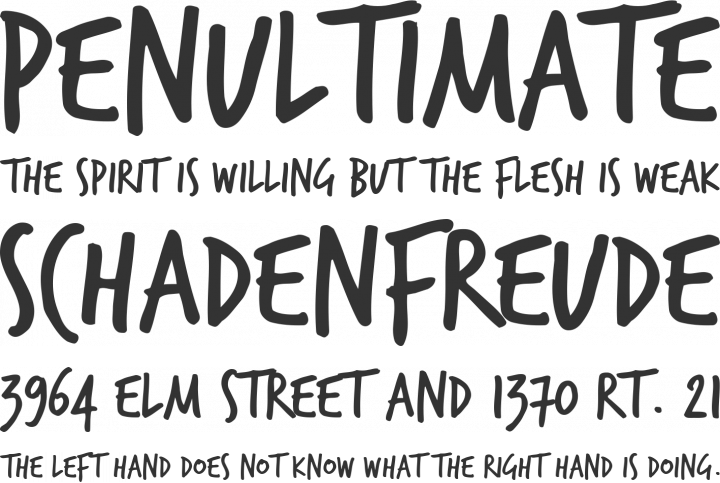
Modewelle: Condensed Comic-Schriften in All Caps und Small Caps für Nahrung, Gaststätten und Genuß (NGG)??
:tuschel: Es geht ja auch nicht um Marker-Schriften, sondern um "Modewelle: Condensed Comic-Schriften …"
Uwe, blättere doch mal in diesem Blog etwas in die Vergangenheit:
Die Annette hat das Aufkommen dieser bestimmten Kategorie ebenfalls sehr früh registriert.
Mindestens ein Korrekturdurchgang hätte nicht geschadet. Nicht nur wegen der vielen Schreibfehler. Nur drei Anmerkungen:
Seite 26: Der Retro-Look, der heute Vintage heißt, brachte damals auch
das alten Handwerk wie Letterpress, was in deutscher Sprache schon
vor Gutenberg profan Briefdruck genannt wird, wieder inMode.
Kleiner Hinweis, weil es mein Gebiet ist: »Letterpress« als Prägedruck ist seit 2009 breit etabliert, das war das erste Jahr, in dem ich mehr davon druckte als vom Bleisatz und die Zahl neuer Werkstätten deutlich höher wurde. Buchdruck (nicht »Briefdruck«) mit beweglichen Lettern vor Gutenberg gab es nicht. Der Mann hat das erfunden. Was sollte an dem Begriff profan sein?
S. 28: Vorsicht mit der
Nutzung dieses Designs, besonders wenn es um nicht kommerzielle
und/oder gemeinnützige Projekte geht. Das Design kann vom Betrachter
mit Gewinnerzielungsabsichten bis hin zur Gier assoziiert
werden.
Ob ich das den Desigern von Hochzeitseinladungen wirklich sagen sollte?
S. 31: So benutzteMc Donalds eine Pinselschrift aus
einem dieser Pakete und Lindt-Schokolade plünderte für sein Design
die kompletten Setzkästen.
Ein deutscher Antiqua-»Setzkasten« enthält 125 Fächer für die Zeichen einer Schrift in einem Schnitt und einer Größe. Viel zu »plündern« gibt es da nicht.
Mindestens ein Korrekturdurchgang hätte nicht geschadet. Nicht nur wegen der vielen Schreibfehler.
Geduld! Rechtschreibung wird überbewertet und das sind erst mal nur Notizen. Wichtiger sind noch die inhaltlichen Fehler, da ich beim Abfassen immer irgend wann mal betriebsblind werde. Ich habe daher Deine drei Kritikpunkte durchgelesen und zwei davon auch schon berücksichtigt. Möglicherweise kommt noch der eine oder andere Hinweis.
Seite 26: Der Retro-Look, der heute Vintage heißt, brachte damals auch
das alten Handwerk wie Letterpress, was in deutscher Sprache schon
vor Gutenberg profan Briefdruck genannt wird, wieder inMode.
Kleiner Hinweis, weil es mein Gebiet ist: »Letterpress« als Prägedruck ist seit 2009 breit etabliert, das war das erste Jahr, in dem ich mehr davon druckte als vom Bleisatz und die Zahl neuer Werkstätten deutlich höher wurde. Buchdruck (nicht »Briefdruck«) mit beweglichen Lettern vor Gutenberg gab es nicht. Der Mann hat das erfunden. Was sollte an dem Begriff profan sein?
Eingebaut ... Hinweis auf Briefdruck verworfen und Definition Letterpress von 2009 nachgetragen.
Der Retro-Look, der heute Vintage heißt, brachte damals auch
das Handwerk wie Letterpress wieder in Mode. Mit Letterpress sind
seit etwa 2009 Akzidenzen mit Prägedruck gemeint.
S. 31: So benutzteMc Donalds eine Pinselschrift aus
einem dieser Pakete und Lindt-Schokolade plünderte für sein Design
die kompletten Setzkästen.
Ein deutscher Antiqua-»Setzkasten« enthält 125 Fächer für die Zeichen einer Schrift in einem Schnitt und einer Größe. Viel zu »plündern« gibt es da nicht.
Ok, ich meinte den kompletten Bestand an virtuellen Setzkästen, also das komplette Paket an Schriften.
Anfang 2016 tauchten die ersten Schriften und Kombinationen aus
solchen Paketen auf. So benutzte Mc Donalds eine Pinselschrift aus
einem dieser Pakete und Lindt-Schokolade plünderte für sein Design
die kompletten Bestände an verfügbaren virtuellen Setzkästen.
Änderungen eingehäckselt ... und irgend wann mal wird richtig probegelesen und korrigiert ... Aber im Moment sind das nur private Notizen, welche vielleicht dem Einen oder der Anderen ein paar Hinweise geben können.
Der Hinweis auf die Gier Seite 28 bleibt erst mal. Und bei Hochzeiten kann durchaus mal Gier dahinter stecken? Mir ist die Problematik der ausbrechenden Stile und der damit wegfallenden Verbindungen, also der Entfremdung von den Wurzeln, durchaus klar. Mit jeder weiteren Entfremdung von der Herkunft gehen immer mehr der traditionellen Werte und Eigenschaften verloren. Aber wie soll man das in kurzen Worten da reinflicken ohne den Leser zuzuschwallen?
Passt ziemlich perfekt ins beschriebene Schema für dieses Design. Bisher hatte ich die Öko-Tripper noch nicht im Blickfeld. Ich werde da ein Auge darauf werfen. Allerdings würde die diese Welle seit spätestens 2016 als abgelaufen betrachten wollen. Die fetten Jahre sind vorbei.
Was beabsichtigst Du eigentlich mit dieser Studie? An wen ist sie gerichtet?
¹ Grafik und Typografie sind  hier als Handwerk zu betrachten, also rein als Werkzeuge.
Ein bisschen will ich damit auch die systematische Analyse solcher Stile aufzeigen. Ich unterscheide grundsätzlich und aus Überzeugung nicht zwischen Propaganda, Werbung und Missionierung. Es soll der Leser in diesem Fall nachvollziehen können wie er verar$cht wird. Aus der Diskussion hier konnte ich einiges lernen und ich gehe davon aus, dass auch der Eine oder die Andere etwas Nutzen daraus ziehen konnte. Wer die versteckte Manipulation erkennen kann, das kann versuchen gegen zu steuern.